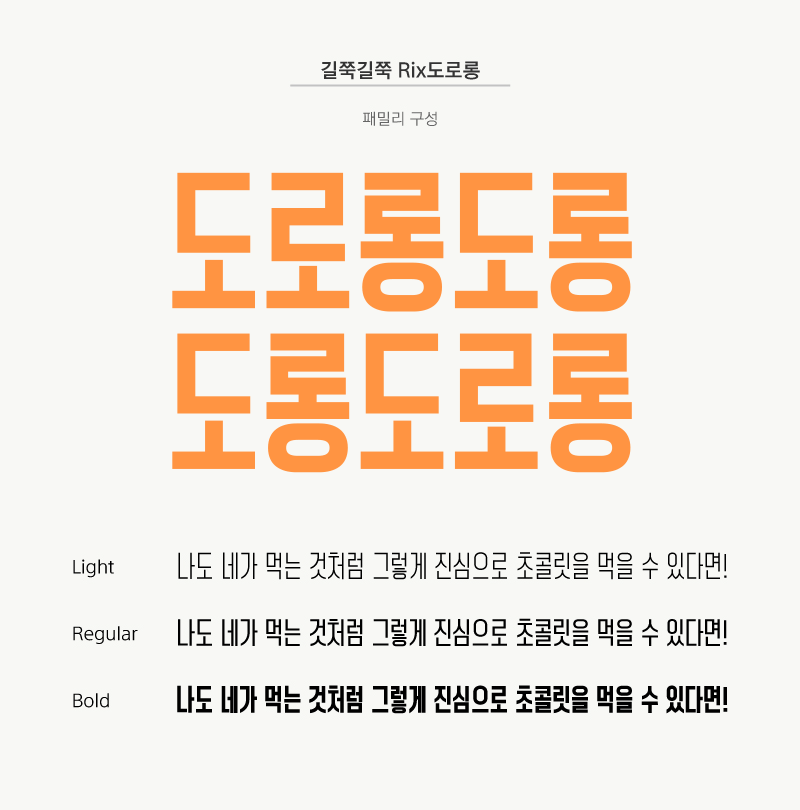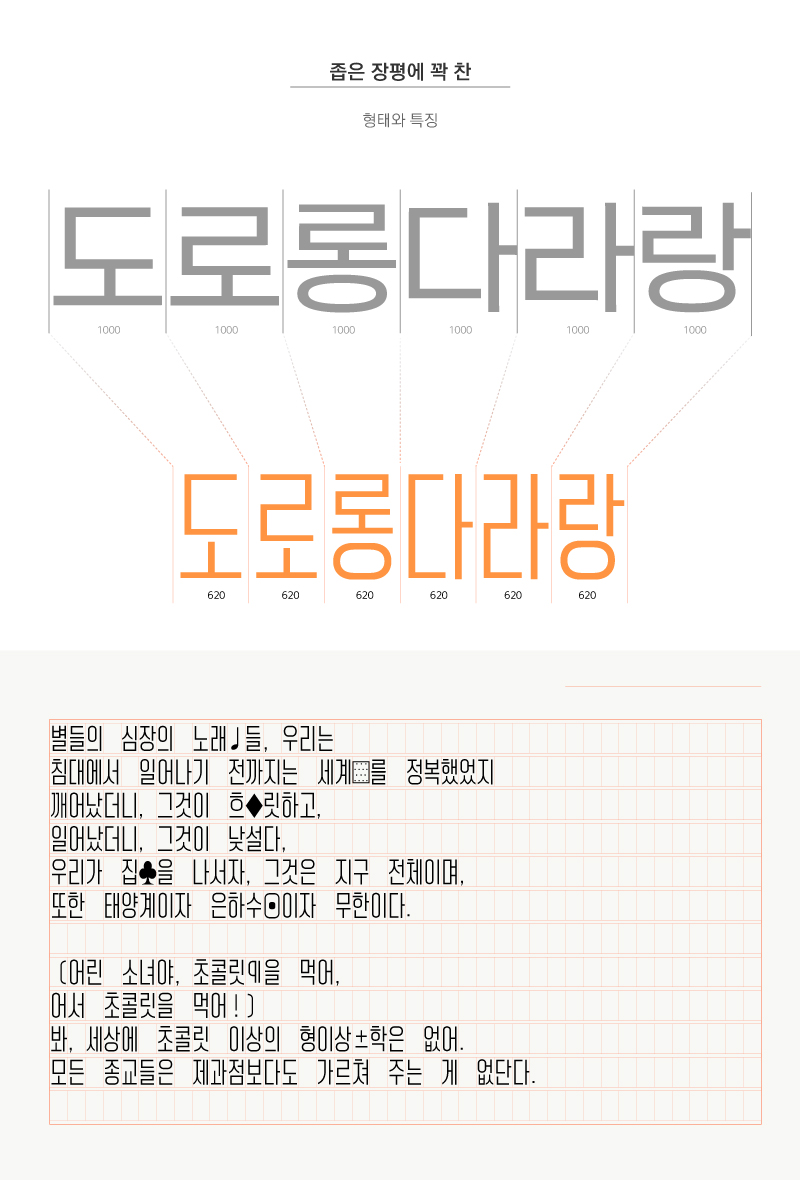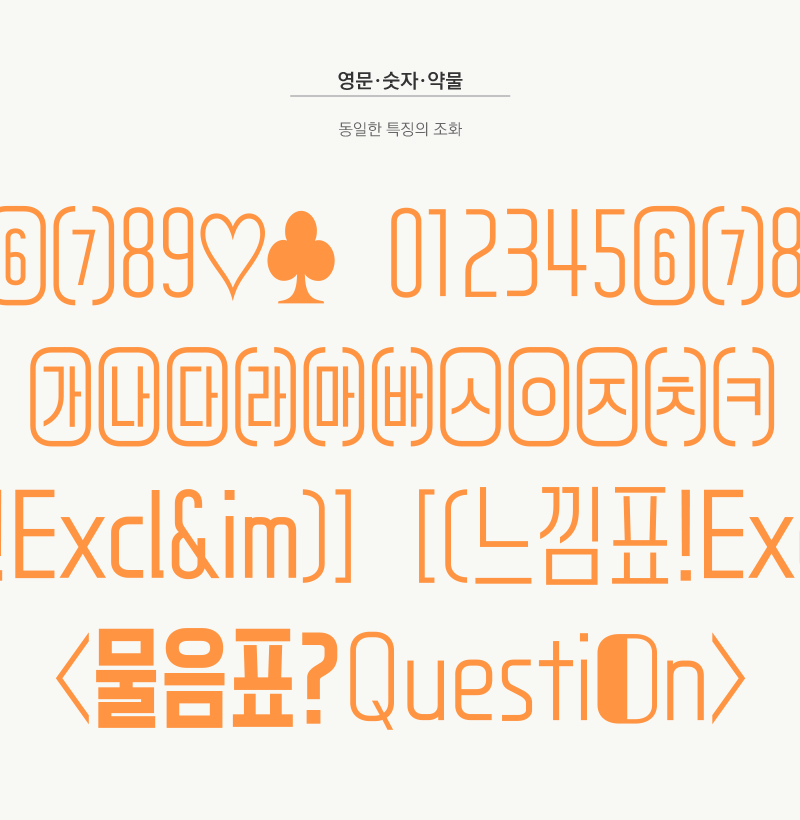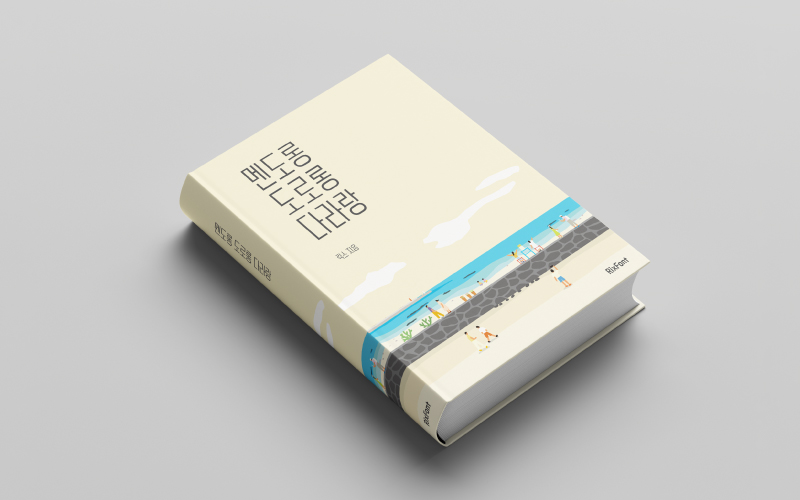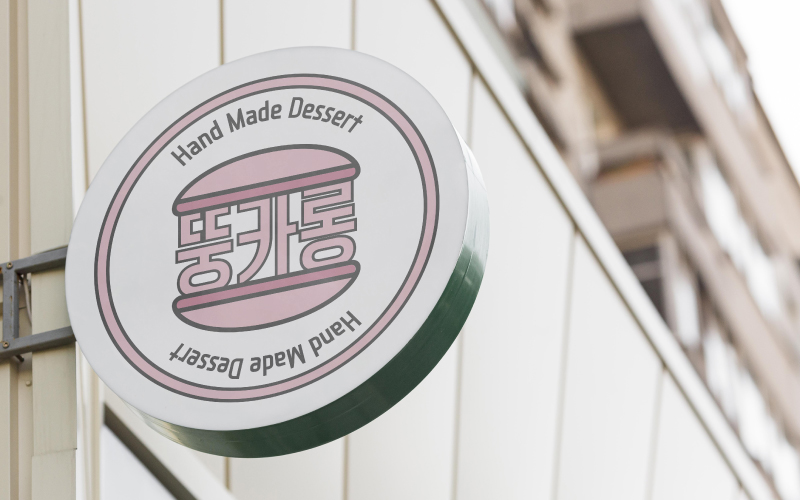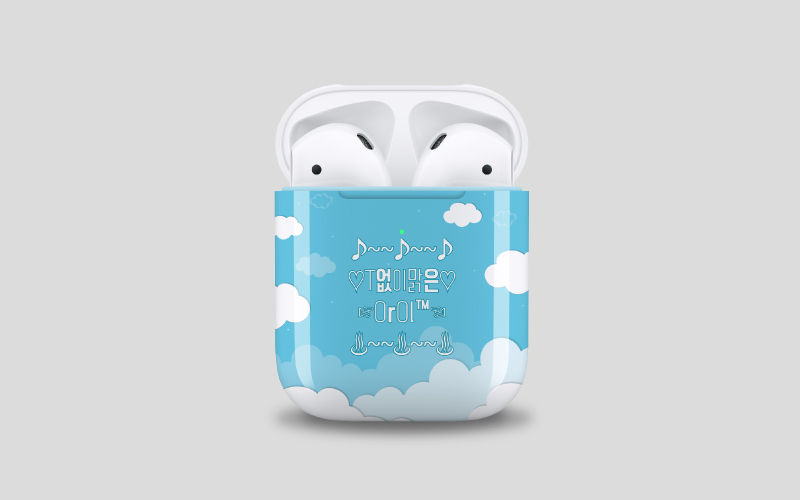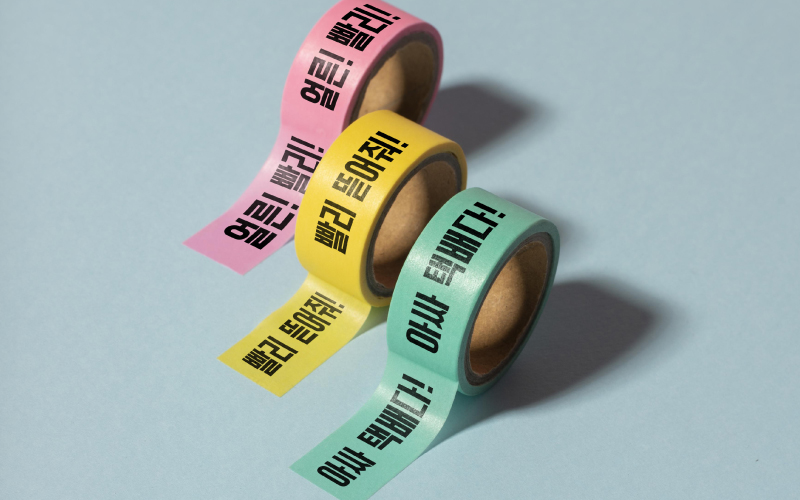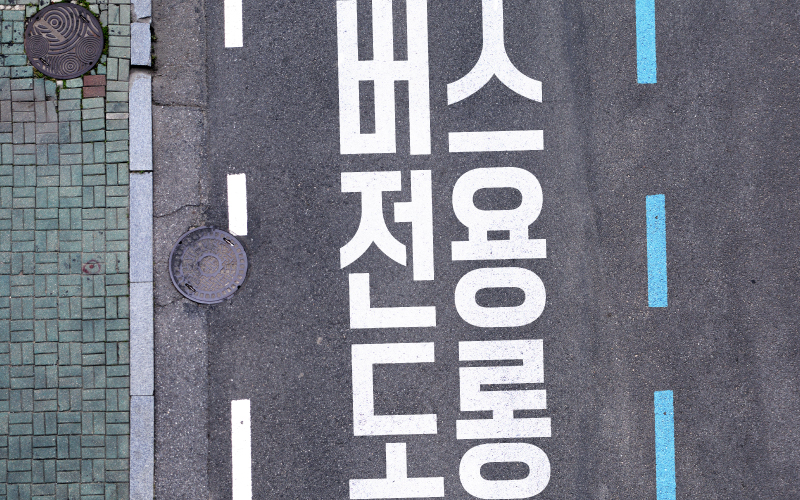
Rix도로롱
3 종 - Bold, Regular, LightRix도로롱은 글자 폭이 좁은 장체 스타일로 심플하고 모던한 형태가 특징입니다.
직선으로 뻗은 획이 시원시원하고 깔끔한 인상을 주며 두께에 따라 색다른 표현이 가능합니다.
3가지 굵기로 제작해 각종 인쇄물, 영상의 제목 및 본문 등 다양하게 활용하기 좋습니다.
| 폰트명 | Rix도로롱 / RixDororong |
| 폰트디자인 | 박용락, 유현주 |
| 디자인디렉팅 | 박용락 |